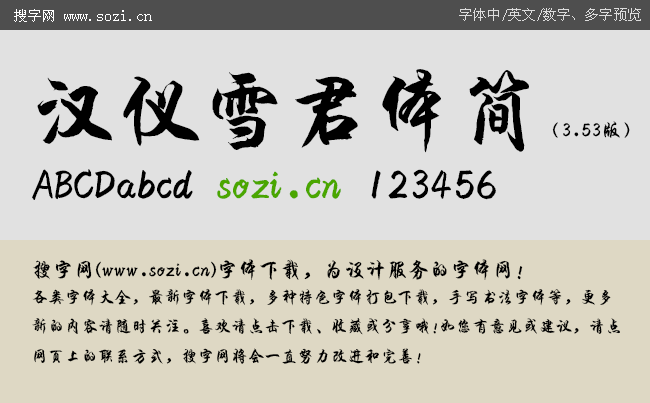
漢儀雪君體簡(jiǎn)
搜字網(wǎng)給大家提供一款書法風(fēng)格的漢儀雪君體簡(jiǎn)體字體下載。漢儀雪君體簡(jiǎn)體由中國(guó)書法家譚學(xué)軍創(chuàng)作并書寫、漢儀公司開發(fā)。實(shí)用性較強(qiáng),比已有的行楷行書味足,顯得更加活潑,筆畫較為粗壯。整副字既嚴(yán)肅又不呆板,流暢大方、雅俗共賞。,此款字體適用于報(bào)刊雜志及書籍、畫報(bào)的主副標(biāo)題和個(gè)性品牌設(shè)計(jì)推廣等環(huán)境。